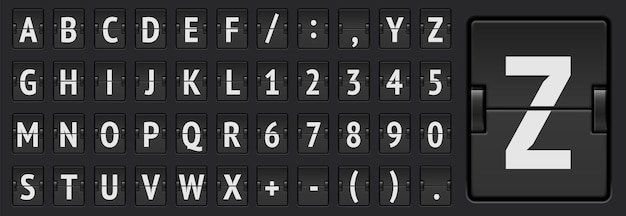
Регулярный алфавит на перекидной доске авиакомпании для отображения информации о пункте назначения или прибытии. Шрифт механического табло терминала аэропорта для отображения информации об отправлении и расписании. Векторная иллюстрация.